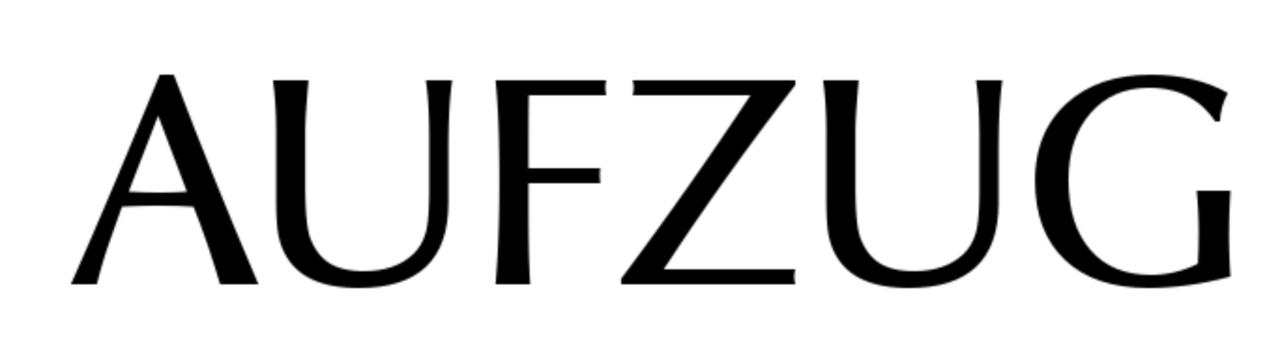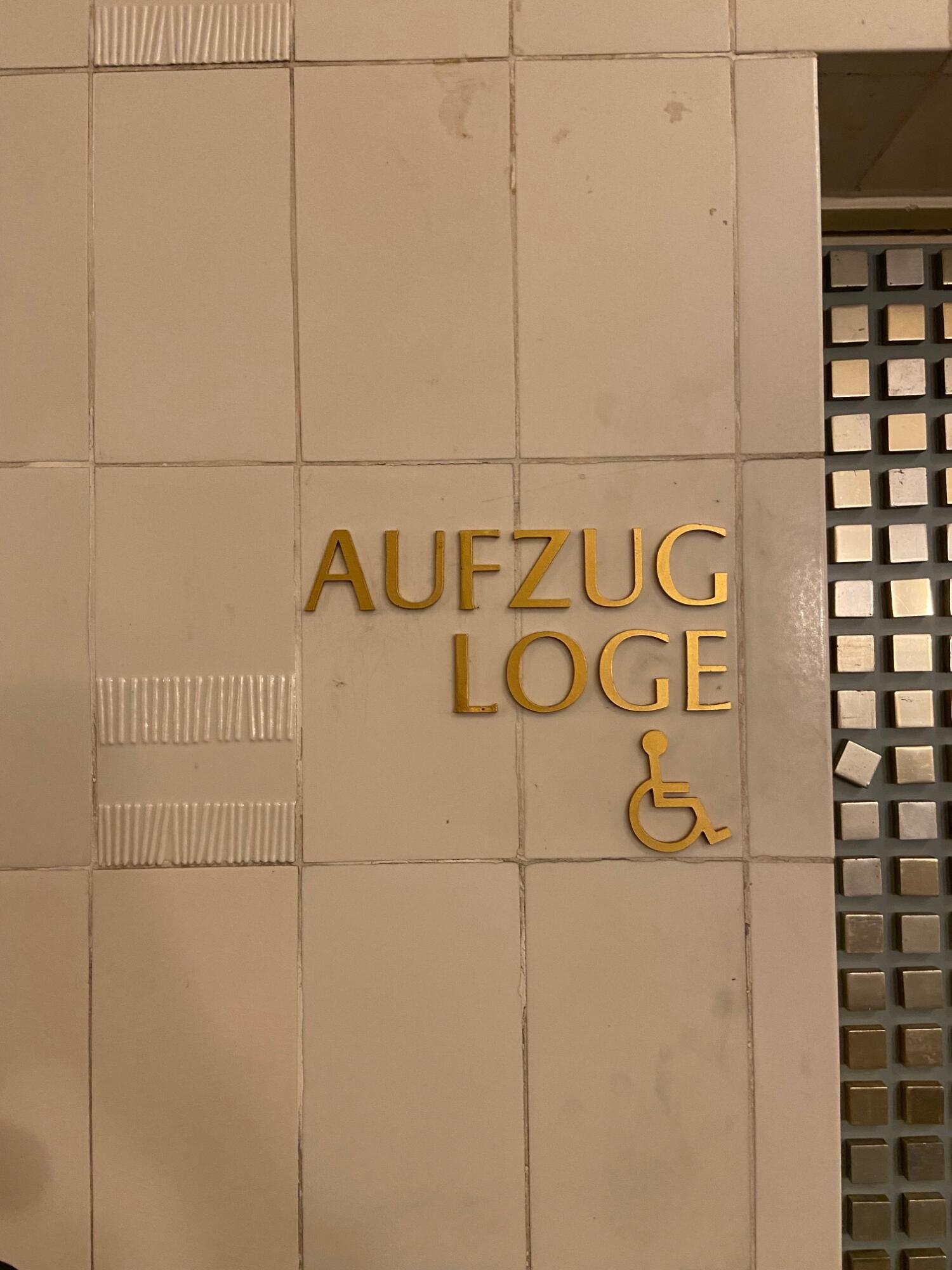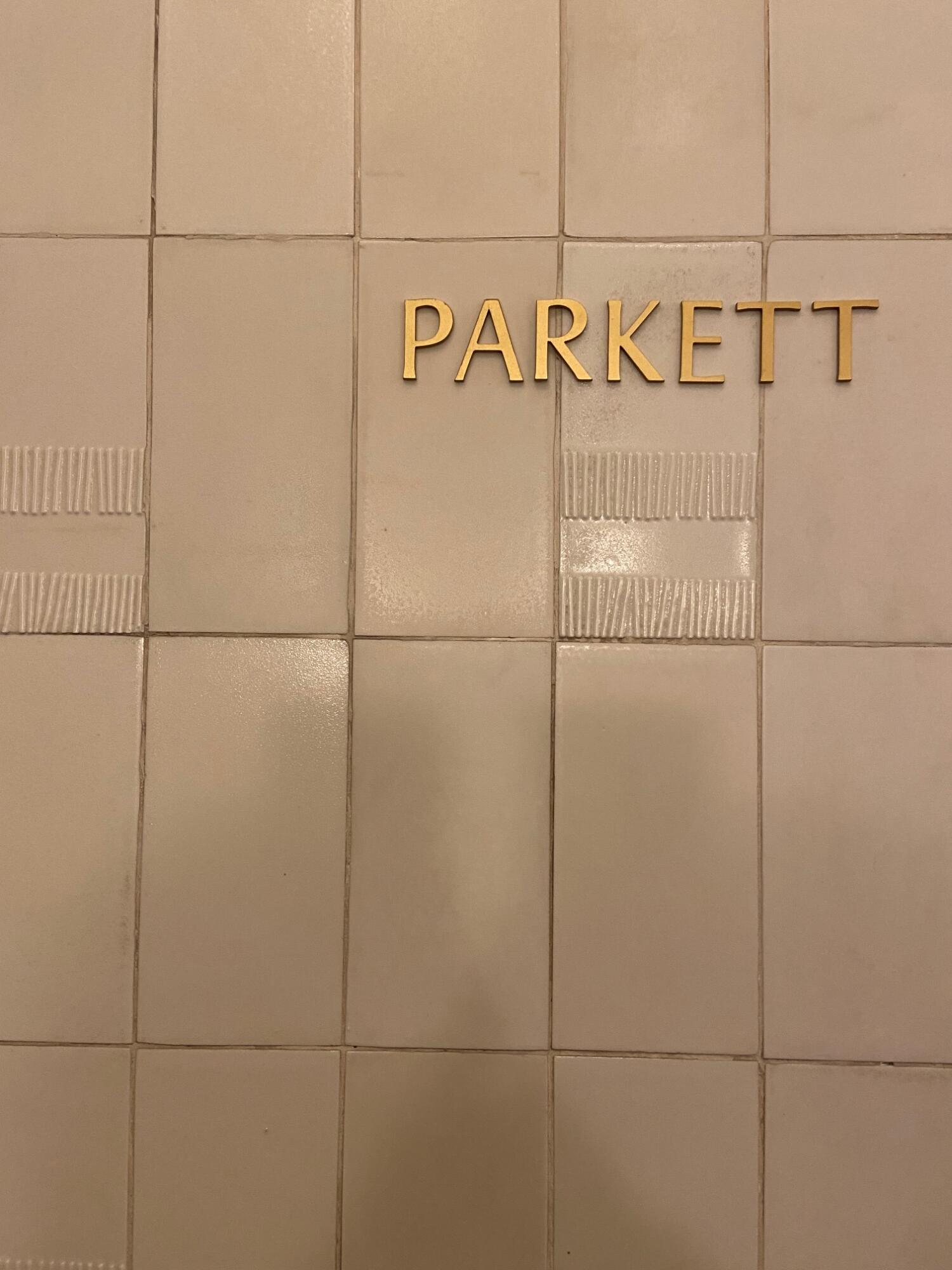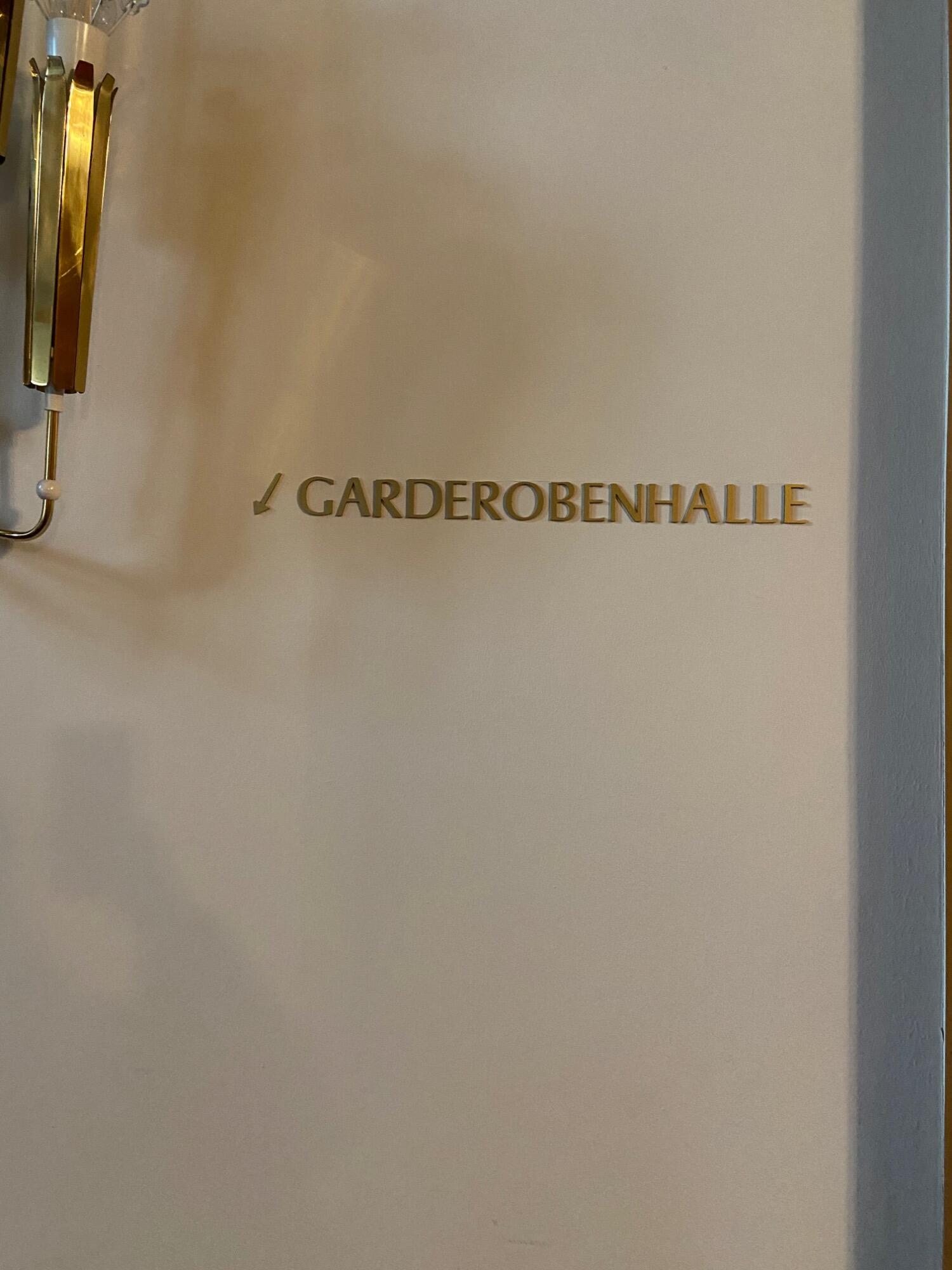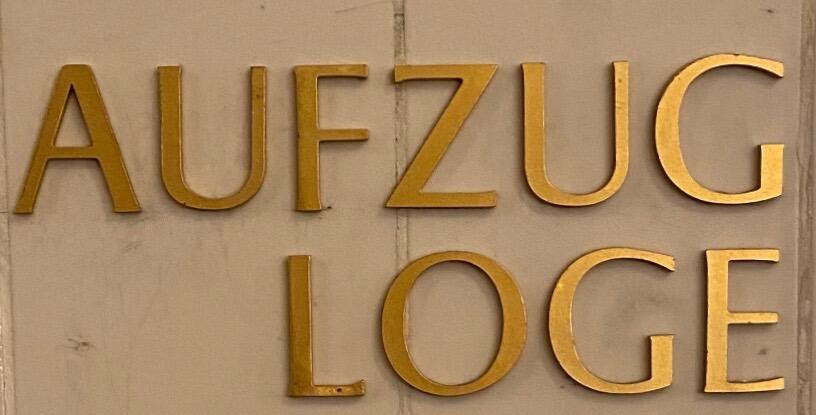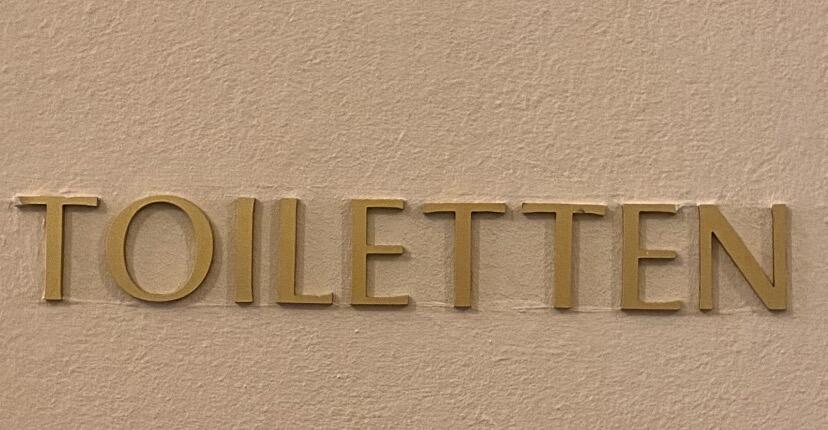
Schriftart Leitsystem Oper Leipzig gesucht.
ich bin auf der Suche nach der Blockschrift der Oper Leipzig (Siehe Foto) Sie wurde 2007 angebracht. Leider gibt es keinerlei weitere Infos. Ich vermute, dass es sich um eine Schriftart handelt, die auch für Grabschriften verwendet wurde.
Sollte es darum gehen diese Beschriftungen zu ergänzen oder zu erneuern sei empfohlen auf Versalausgleich und Kerning zu achten. Da scheint es bisher gemäß der Fotos etwas zu hapern.
Müsste man dazu bohren, okay. Aber beim Kleben kann man sich wunderbar diverser Hilfsmittel bedienen. Etwas mehr Qualitätsanspruch sollte für so ein Haus drin sein.
Möglicherweise war Mitte der 1950er-Jahre in der DDR für solche Feinheiten kein Budget vorhanden. Zumindest sehen mir die Buchstaben nicht so aus, als wären sie bei der Sanierung neu gemacht worden.
Aus der Ferne wird das alles Spekulation bleiben müssen. Aber es wird ja unzählige Fotos aus dem Innenbereich über die Jahrzehnte hinweg geben. Damit könnte man sicherlich bestimmen, wann diese Art der Beschriftung nun definitiv ins Haus kam. Es würde mich jedenfalls auch nicht wundern, wenn es direkt oder indirekt auf Arbeiten aus der DDR-Zeit zurückgeht und damit wären wir in der vordigitalen Zeit, wo solche 3D-Buchstaben nicht einfach aus Druckschriften gefertigt wurden. Die Unterschiede zur sicherlich Pate stehenden Optima wären dann keine Überraschung.